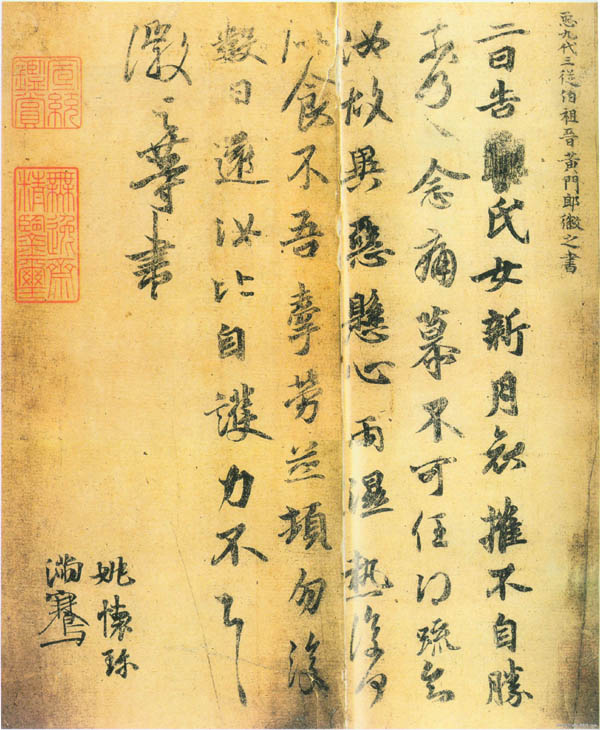
王徽之
王徽之简介
字子猷,羲之子,弟王献之,文章为世人所推崇,善书画。子猷生性卓荦不羁,性好竹。时人钦其才而秽其行。后为黄门侍郎,弃官东归。
《新月帖》,见于辽宁省博物馆藏的《唐摹万岁通天帖》,传为王徽之书,唐摹本。此帖以行楷为主,挥洒自如,笔法多变,妍美流畅。宋《宣和书谱》。评其书法“作字亦自韵胜”。
释文:
臣九代三从伯祖晋黄门郎徽之书
二日,告□氏女,新月哀摧不自胜,
奈何奈何。念痛慕,不可任。得疏知
汝故异恶悬心,雨湿热复何
似,食不?吾牵劳并顿,勿复,
数日还,汝比自护。力不具。
徽之等书。
姚怀珍,
满 骞。